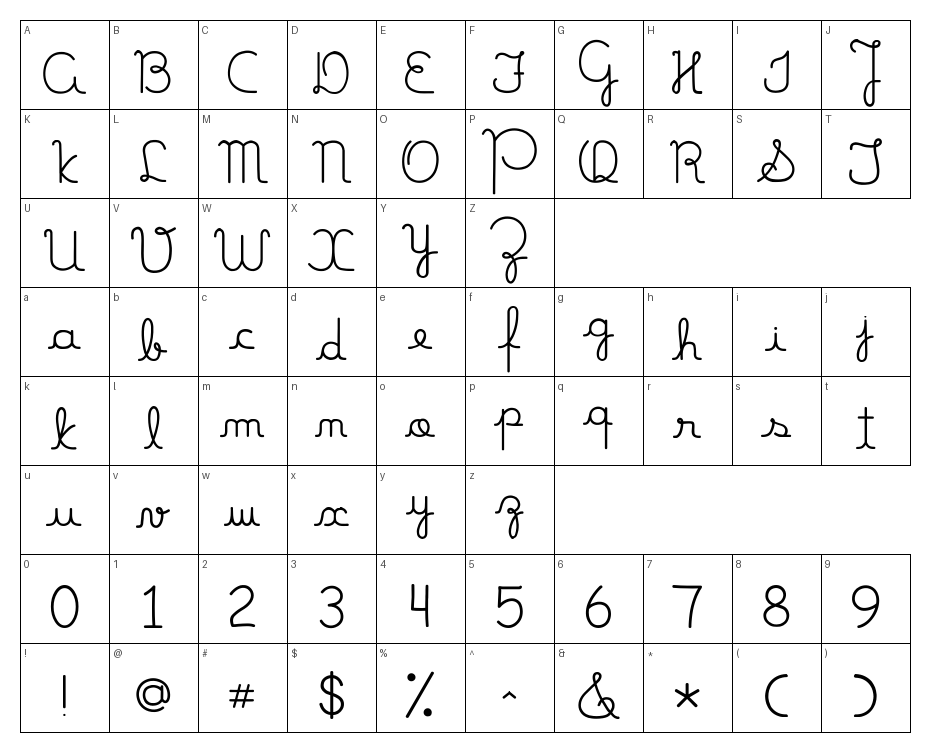
Fonte criada para caligrafia em colégios e educandários. Criada especialmente para minha mãe que é professora.
Schriftname: Mamãe Que Nos Faz
Name des Designers: Rafael Pereira